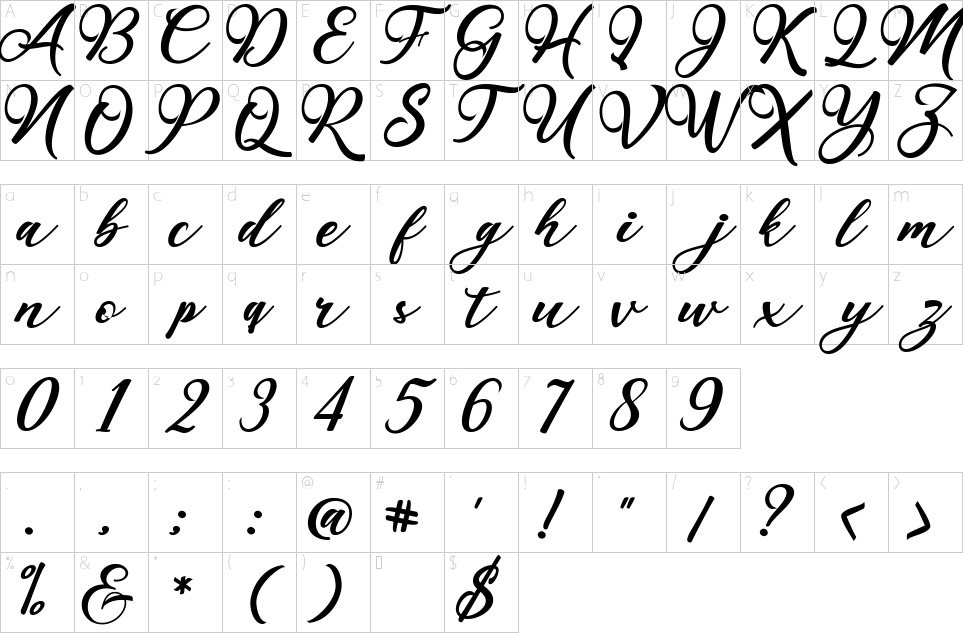
A fonte Maulie Script é uma opção grata para aqueles que desejam dar um toque elegante e sofisticado a suas criações digitais. Desenvolvida pela designer desconhecida Gatype, esta fonte vem para aqueles que buscam um estilo romântico e legível. Com um design cuidadosamente elaborado, a Maulie Script se destaca em suas capacidades de escrita, oferecendo um estilo gráfico fluido e elegante. Não importa se você está trabalhando em um projeto para o desktop ou um aplicativo para Mac, a fonte Maulie Script tem algo para todos, permitindo que seus designs sejam tanto criativos quanto sofisticados. Com mais de 660 downloads, é fácil ver a popularidade e o valor desta fonte de script. Descubra a diferença que a Maulie Script pode fazer em seus projetos digitais, oferecendo uma dose de elegância e personalização para cada projeto.